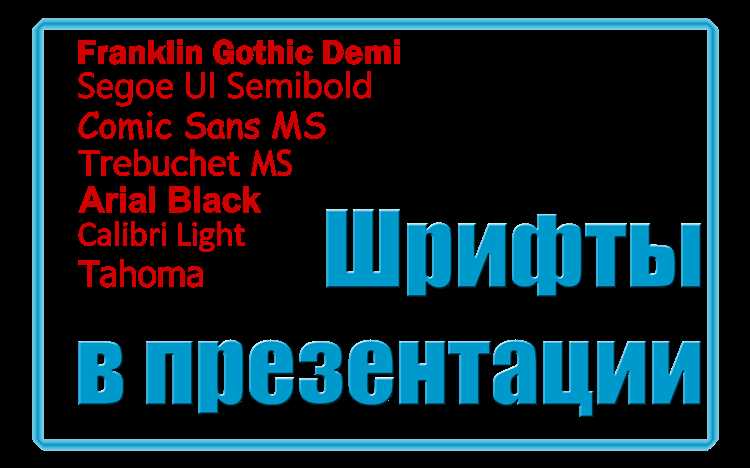
Требования к оформлению презентаций в PowerPoint для государственных и образовательных учреждений регулируются рядом стандартов, в том числе ГОСТ 7.32–2017 и ГОСТ Р 7.0.97–2016. В них нет прямого указания на конкретный шрифт, однако есть требования к его читаемости, строгости и отсутствию декоративных элементов. На практике применяется гарнитура, соответствующая этим критериям – Arial.
Arial – шрифт без засечек, включён в стандартный набор Windows и поддерживается на всех устройствах. Его выбор обусловлен тем, что он визуально нейтрален, хорошо читается с экрана и соответствует требованиям к деловому стилю. Для заголовков допустимо использование Arial Bold, но без изменения гарнитуры.
Размер шрифта в соответствии с методическими рекомендациями: не менее 18 pt для основного текста, не менее 24 pt для заголовков. Цвет текста – преимущественно чёрный или тёмно-синий на светлом фоне. Применение курсивов, подчёркиваний и других выделений допускается только при необходимости акцента на ключевой информации.
Презентации, оформленные с отклонением от этих норм, могут быть отклонены при сдаче отчётов, защитах дипломов или выступлениях в официальных учреждениях. Поэтому важно соблюдать предписанные параметры не только формально, но и с учётом визуального восприятия.
Какой шрифт соответствует требованиям ГОСТ для текстов в слайдах
Согласно ГОСТ Р 7.0.97–2016 и ГОСТ 2.105–2019, для оформления текстовой информации рекомендуется использовать простой шрифт без засечек, обеспечивающий разборчивость с экрана при проецировании. На практике основным вариантом считается Arial.
Arial соответствует требованиям ГОСТ по следующим параметрам: отсутствие засечек, чёткое отображение символов, одинаковая толщина линий, высокая читаемость при масштабировании. Он доступен в стандартных установках Windows и не вызывает проблем при передаче файлов между пользователями.
Допускается также использование Calibri или Tahoma, но при этом следует учитывать, что Calibri не упоминается в ГОСТах как предпочтительный, а Tahoma применяется ограниченно из-за плотного начертания. При наличии строгих требований к соответствию стандартам предпочтение следует отдавать Arial.
Размер шрифта для основного текста в слайдах по ГОСТ должен быть не менее 18 пунктов. Заголовки оформляются крупнее – от 24 пунктов и выше, в зависимости от структуры слайда. Шрифт должен быть единообразным на всех слайдах без использования декоративных вариантов.
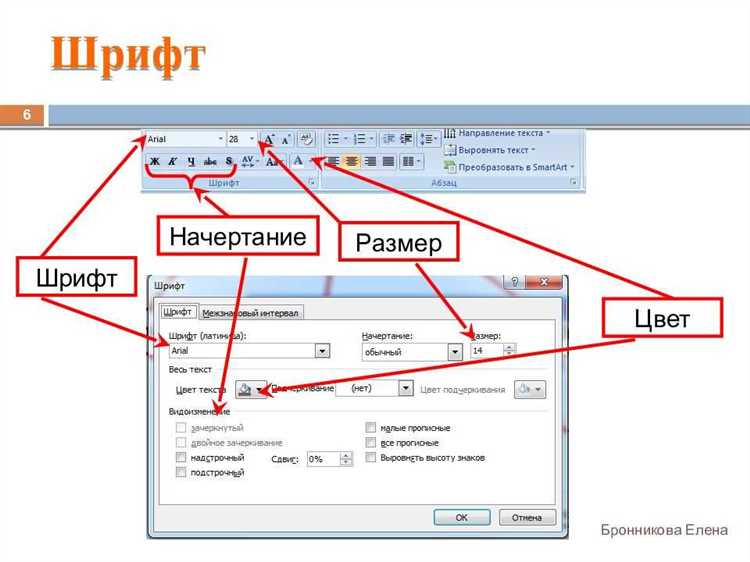
ГОСТ 7.32-2001 и ГОСТ Р 7.0.97-2016 содержат рекомендации по оформлению текстовых документов, включая презентационные материалы. Согласно требованиям, размер шрифта должен обеспечивать читаемость с расстояния не менее 2 метров при проецировании на экран.
Для заголовков применяется размер шрифта не менее 24 пунктов. При этом оптимальный диапазон – 28–36 пунктов, чтобы выделить структуру слайда и сохранить иерархию.
Основной текст должен быть не мельче 18 пунктов. Наиболее подходящий размер – 20–24 пункта. Меньший кегль допускается только для сносок или пояснений, не играющих ключевую роль в восприятии информации.
Важно избегать резких перепадов между размерами шрифта внутри одного слайда. Рекомендуется сохранять стабильную пропорцию между заголовками и текстом, чтобы не нарушать визуальное восприятие.
Цвет и контрастность шрифта по ГОСТ в презентационных материалах
Согласно ГОСТ Р 7.0.97-2016, текст на слайдах должен быть легко читаем при проецировании на экран. Основное требование – достаточный контраст между цветом шрифта и фоном. На светлом фоне используют тёмный шрифт, на тёмном – светлый. Недопустимы сочетания низкой контрастности, например, серый текст на синем фоне или жёлтый на белом.
ГОСТ рекомендует использовать чёрный цвет шрифта на белом или светло-сером фоне как основной вариант. Альтернативой допускается белый текст на чёрном или тёмно-синем фоне. Красный, зелёный и синий цвета используются ограниченно и только для акцентов. Многоцветный текст или декоративные градиенты не соответствуют требованиям стандарта.
Минимальный уровень контрастности должен обеспечивать коэффициент яркости не менее 3:1. Для проекторов с невысокой яркостью рекомендуется выбирать комбинации с максимальным различием светлоты – например, белый фон и тёмно-синий или чёрный текст. Фон с изображениями, градиентами или текстурами затрудняет восприятие и не допускается.
Также ГОСТ указывает, что весь текст должен быть одинакового цвета внутри одного блока, чтобы избежать визуальной нагрузки. Изменение цвета допустимо только для логически обоснованных выделений: заголовков, терминов или акцентов, но не более чем в 10–15% от общего объёма текста на слайде.
Требования ГОСТ к межстрочному интервалу и расстоянию между символами
Согласно ГОСТ 7.32–2017 и ГОСТ Р 7.0.97–2016, межстрочный интервал в текстах презентаций должен составлять от 1 до 1,5. Оптимальным считается интервал 1,15 или 1,5 – для обеспечения читаемости при демонстрации на экране. Интервал менее 1 приводит к слипанию строк, затрудняющему восприятие.
Можно ли применять в презентациях PowerPoint шрифты, отличающиеся от тех, что указаны в ГОСТ?
Да, применение шрифтов в презентациях допускается с учетом удобства восприятия и целевой аудитории. ГОСТ не устанавливает обязательных шрифтов для слайдов, поэтому выбор чаще зависит от внутреннего регламента компании или предпочтений автора. Главное, чтобы текст был четким, легко читался и не отвлекал внимание от содержания. Обычно выбирают простые и нейтральные шрифты, чтобы сохранить деловой стиль.